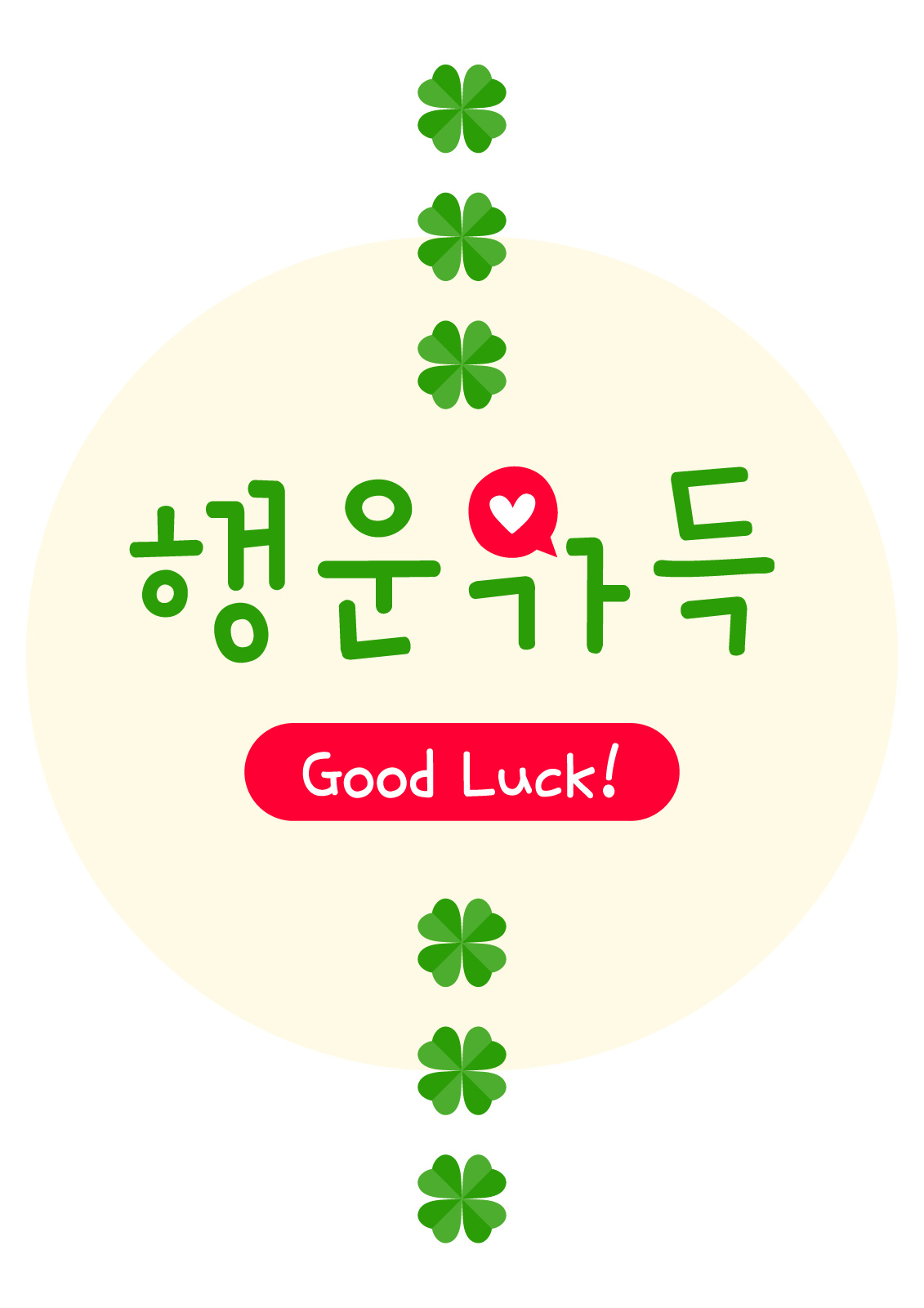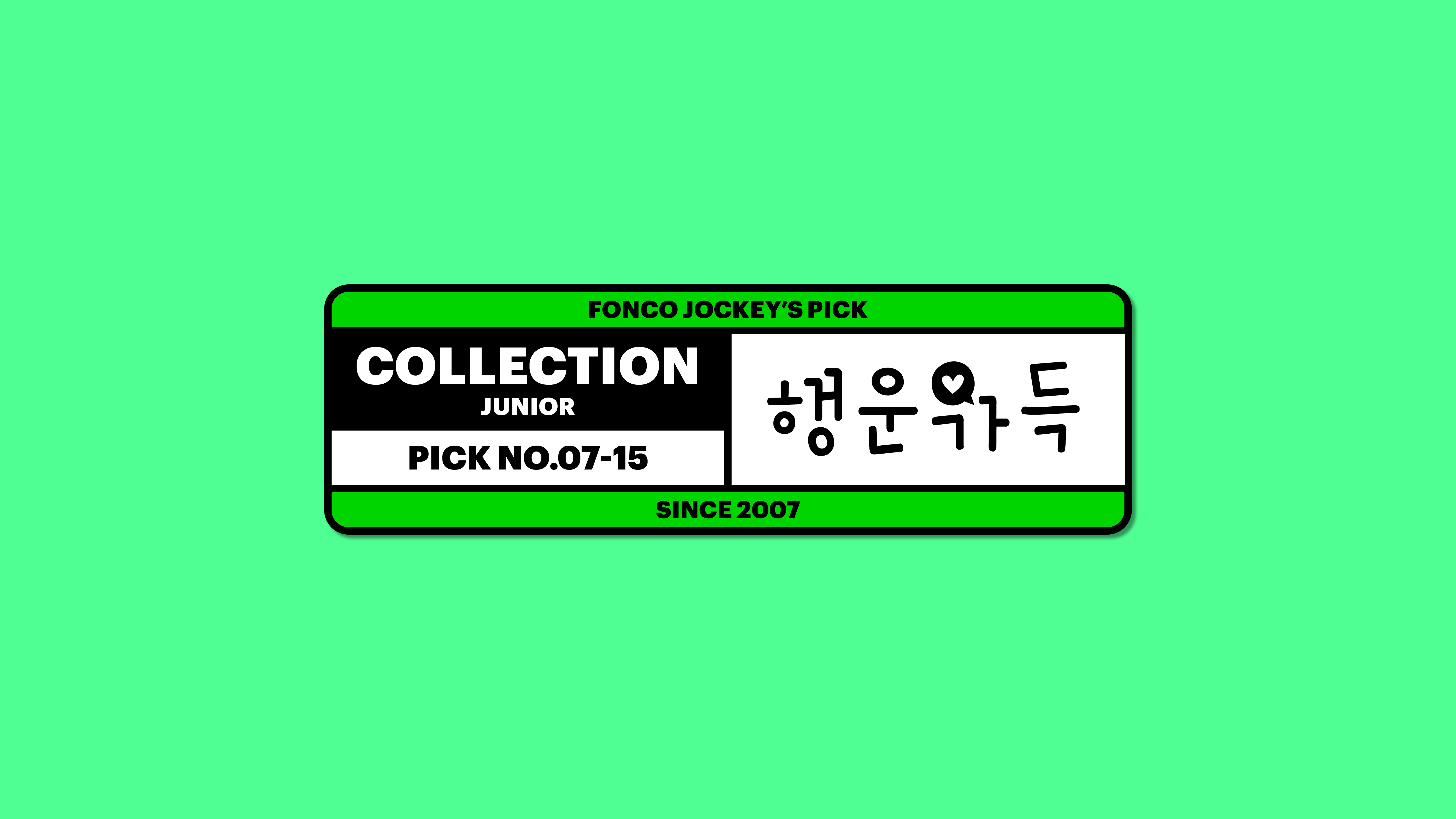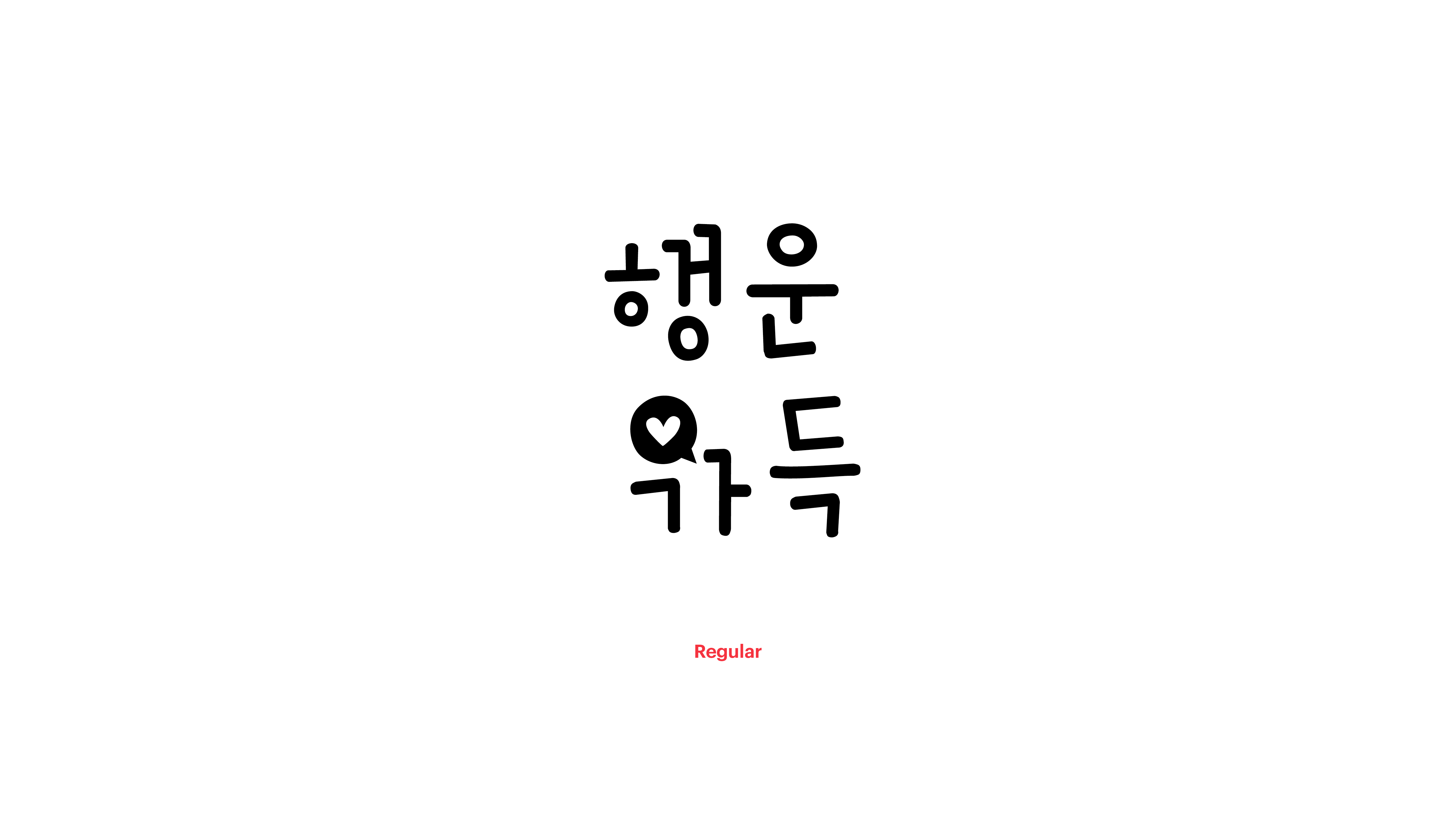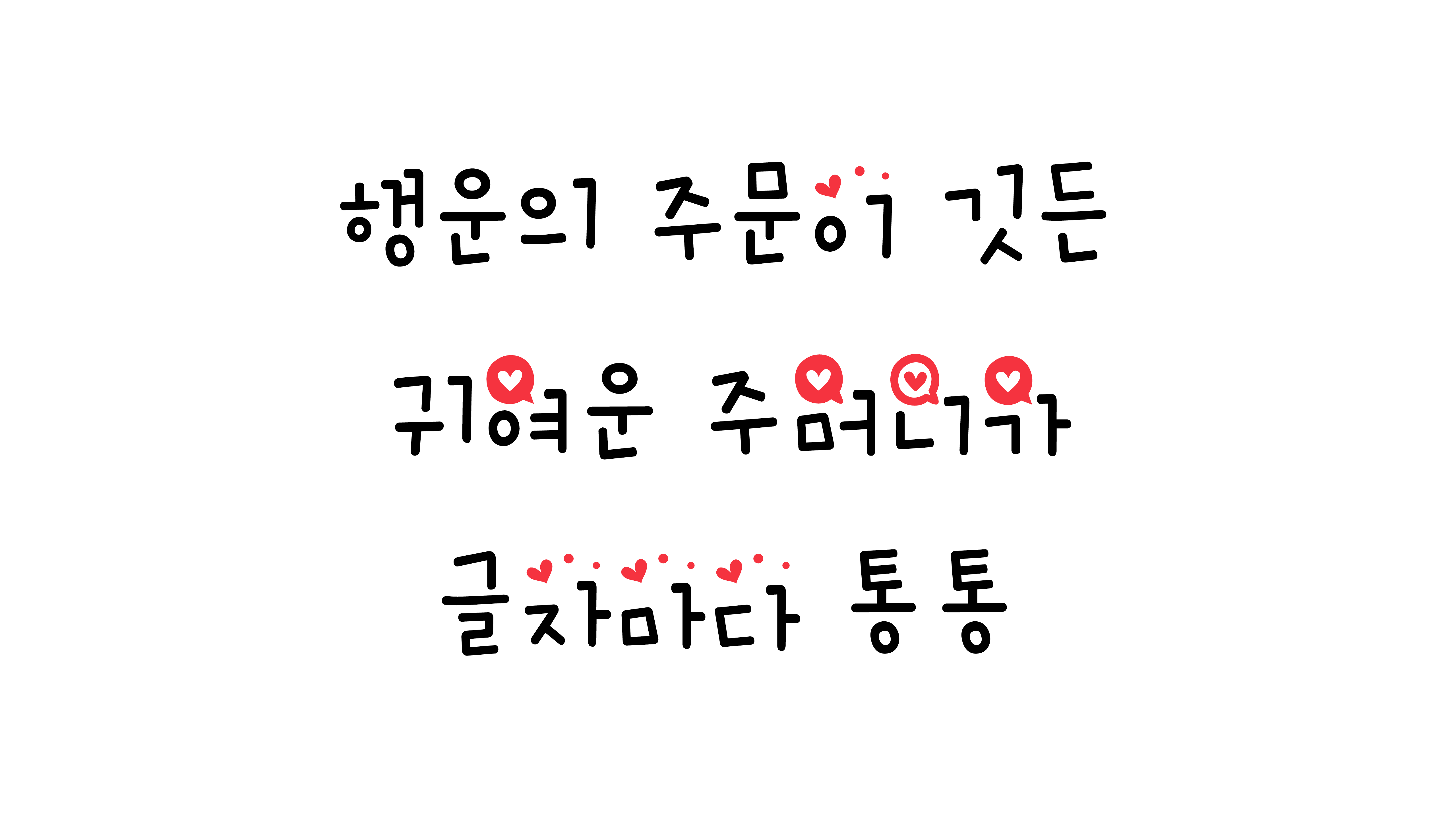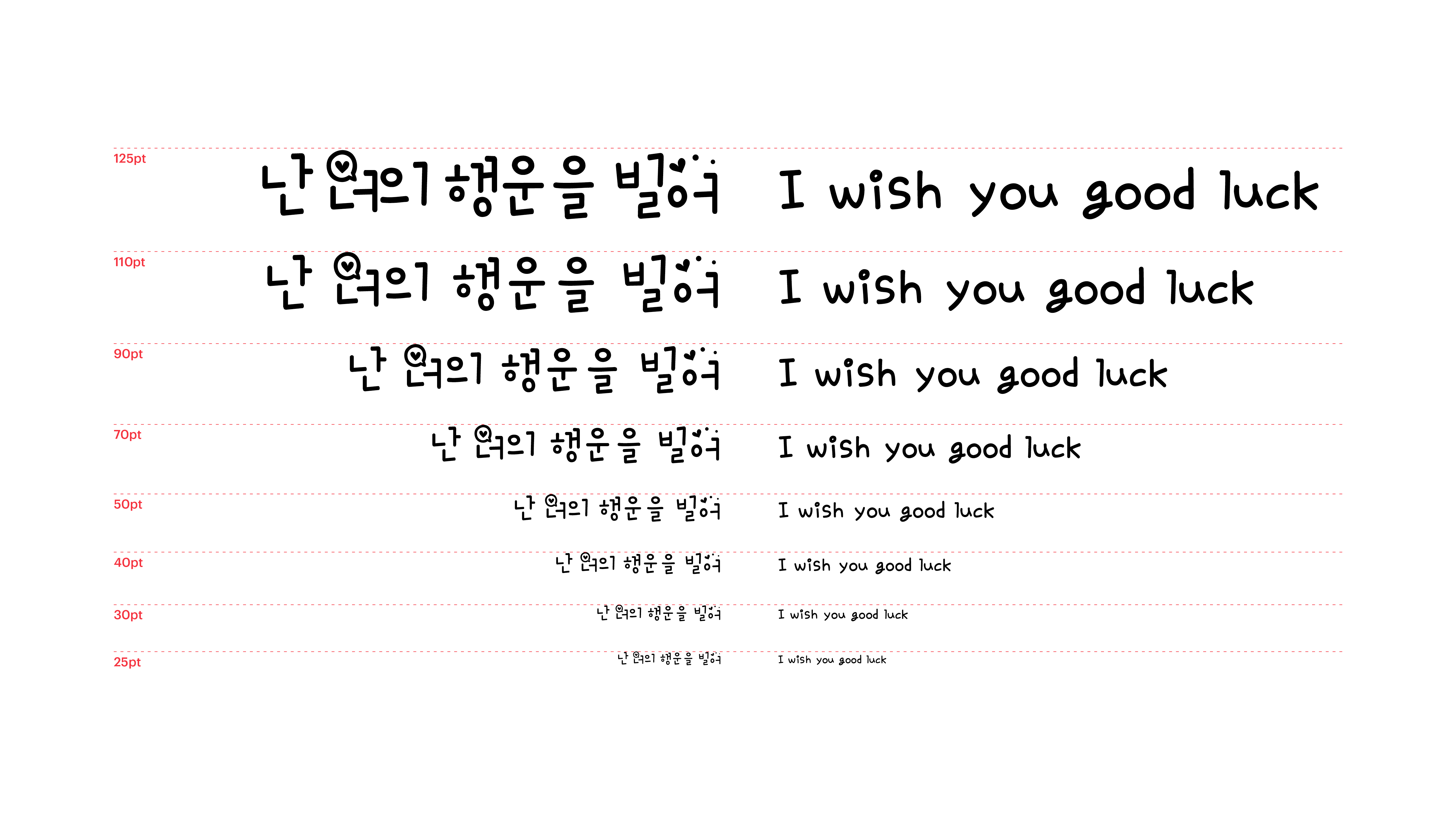
중요한 면접이 있으신가요? 아니, 소개팅이 있으시다고요? 진작 말씀해 주셨더라면 제가 이 폰트를 소개해드렸을 텐데…. 이름 그대로 행운 가득! 행운을 데려올 거라는 믿음을 가지고 제작한 폰트입니다. 행운의 주문이 담긴 귀여운 주머니가 글자마다 뿅, 하고 나타나지요. 그러니 여러분도 믿음을 가지고 사용해보세요. 이제부터 모두 함께 행복해지는 거예요!
Yoon 행운가득